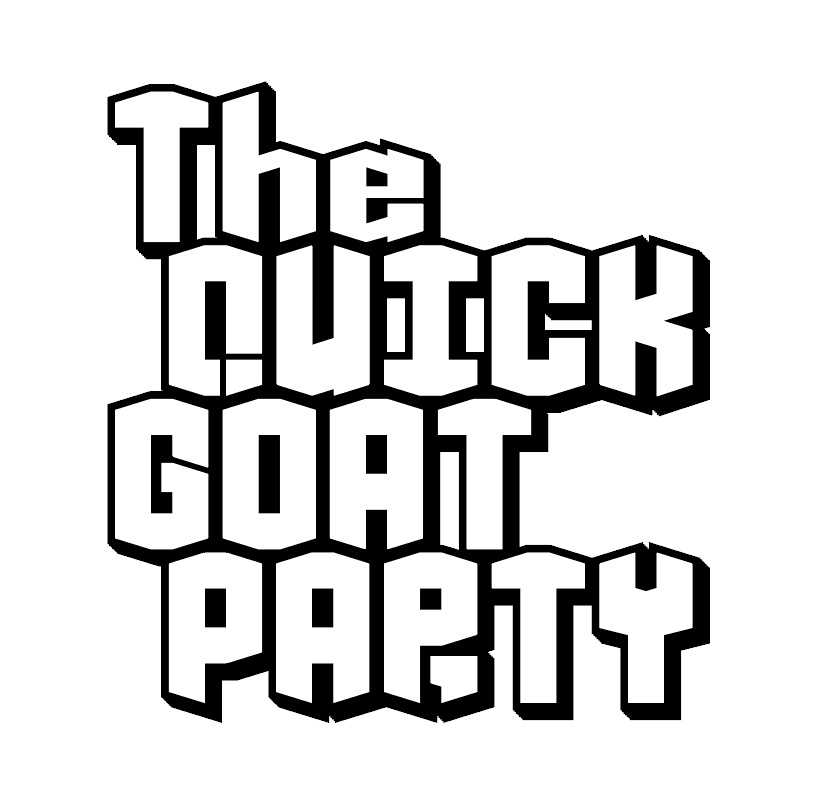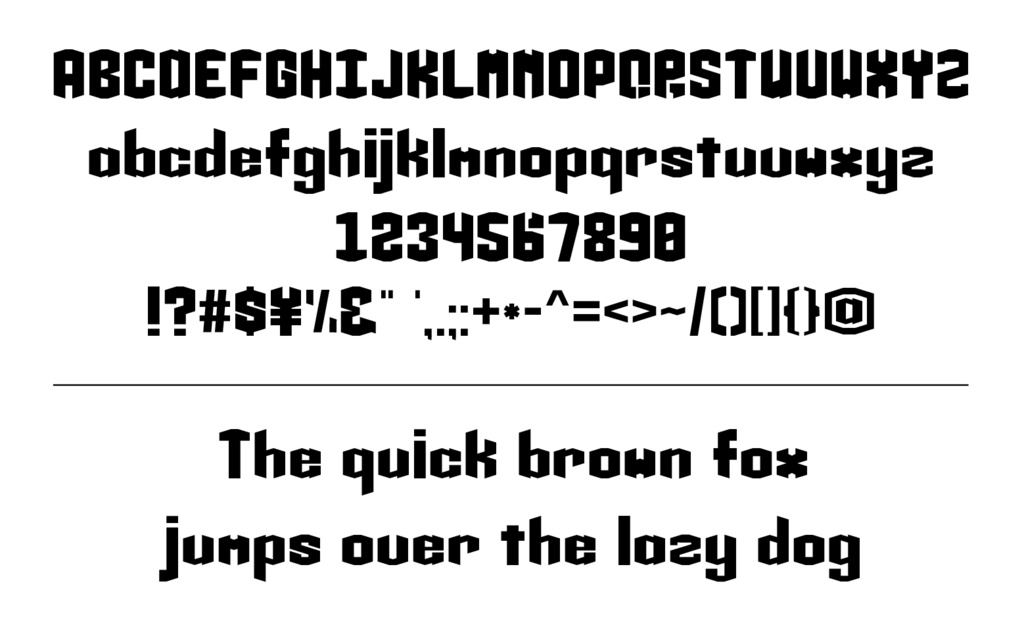
Octagolフォント
●フォントについて ・英数字+記号が含まれたフォントです。 画像のように、スペースを入れることで8角形が噛み合い、パズルのようにできます。 ・ファイル形式はOTF、TTFです。 基本的にどのアプリケーションでも利用できる形式です。 ・名前「Octagol」の由来は、「八角形」を意味する「Octagon」と、黄金比を利用したフォントであるため、「黄金比」から「Gold」を組み合わせ、「Octagol」と名付けました。 ・今後文字の内容や形状等を変更する可能性がございます。 もし変更があっても、一度ご購入された商品は再度ダウンロード可能です。 ■注意事項・詳細 ・個人利用・商用利用は可能です。 ・商品の返品・返金等は不可です。 ・著作権は放棄していません。著作権はすべて、制作者「ようとも」に属します。 ・このフォントを使用することによって生じた、いかなるトラブル・障害・損害についてこちらは一切の責任を負わないものとします。 ・使用報告やクレジット表記不要です。 ・フォントデータをダウンロードした時点で、使用できる範囲・禁止事項等、記載内容に同意したこととします。 ■禁止事項 ・公序良俗に反する利用 ・フォント・フォント制作者の知的財産権を侵害する行為。 ・再販売・改変 ・データの一部、もしくは全部を、加工の有無や有償無償にかかわらず再配布すること、サーバー・SNS・チャット・ネット等へのアップロードなど他者が再利用できる形にすること。 ・webサイト・アプリ等で、第三者がフォントデータを抽出できる状態にすること。 ・フォントを第三者に譲渡・貸与・配布・販売すること。 ・フォントを利用した素材集、データ集、テンプレート集の作成・販売すること。 ・フォントそのものがコンテンツとなる販売物、販促物の販売。 ・データの一部、もしくは全部を、著作権登録・意匠登録・商標登録など知的財産権の登録を行うこと。 ・フォントを利用した文字主体の制作物、ロゴなどの商標登録 ・生成AIなどの学習に使用すること。